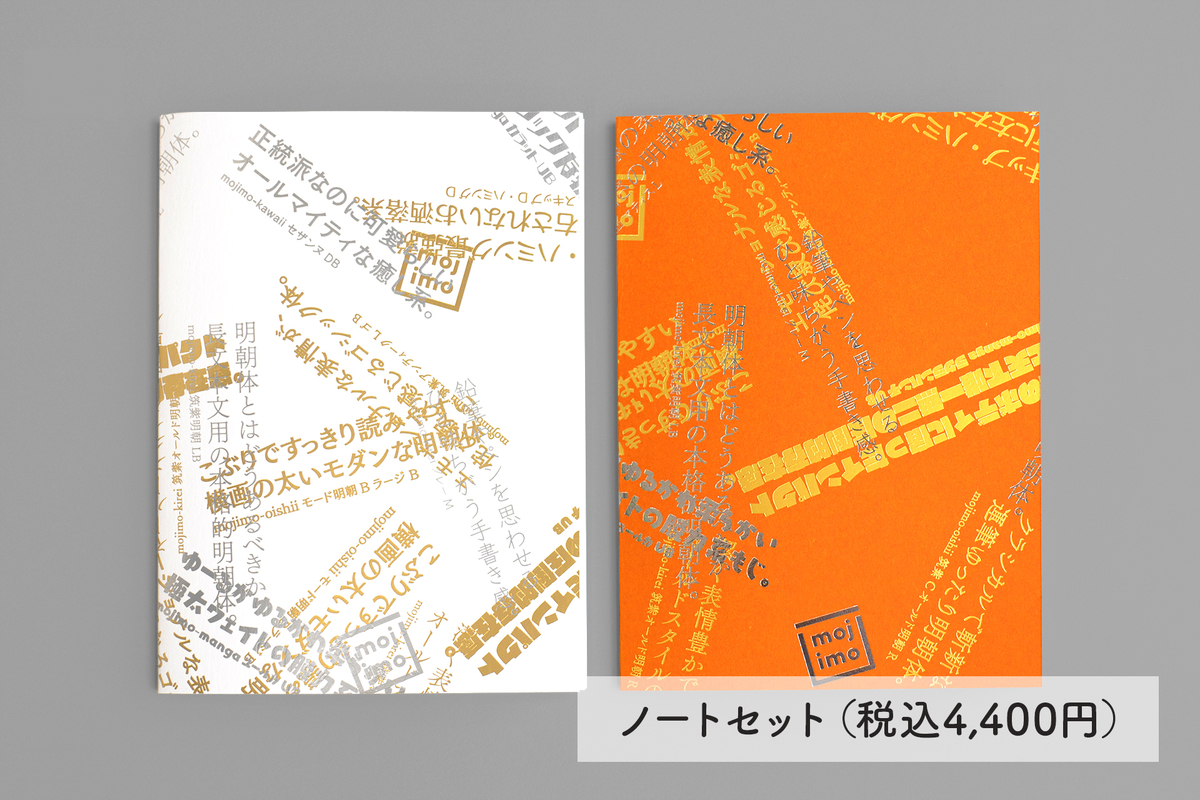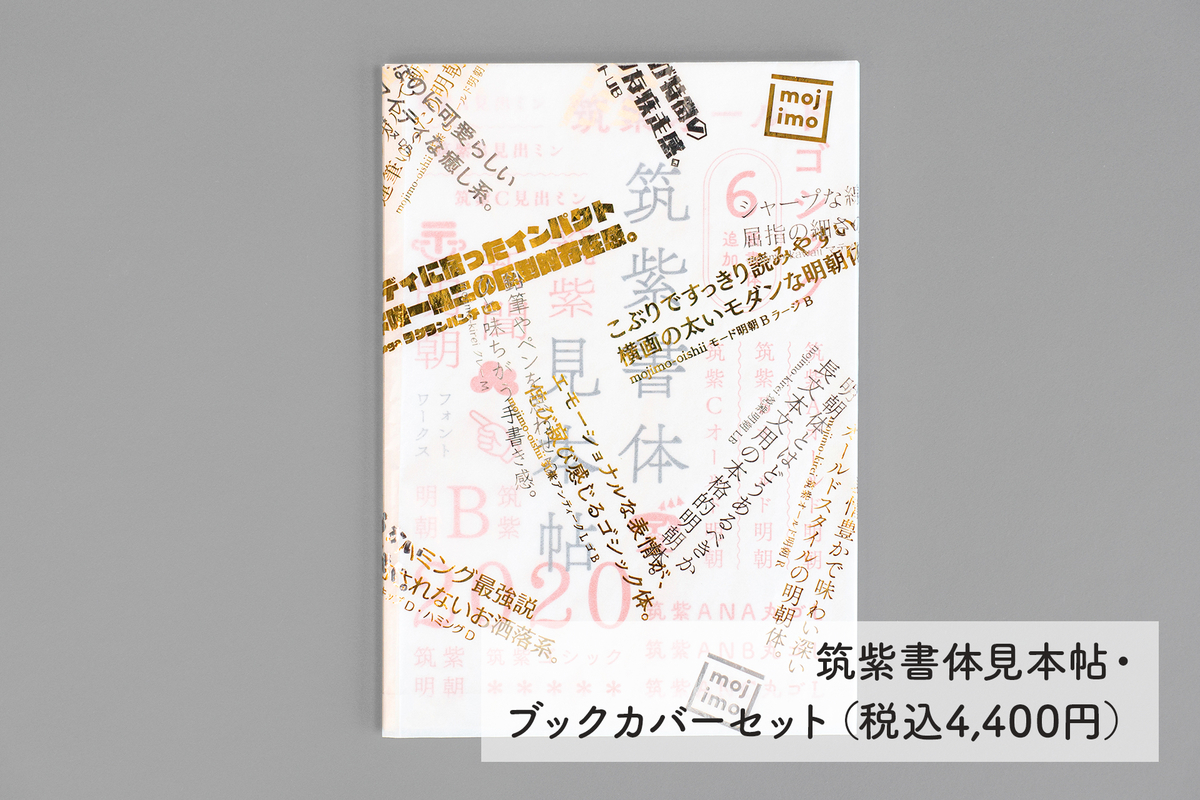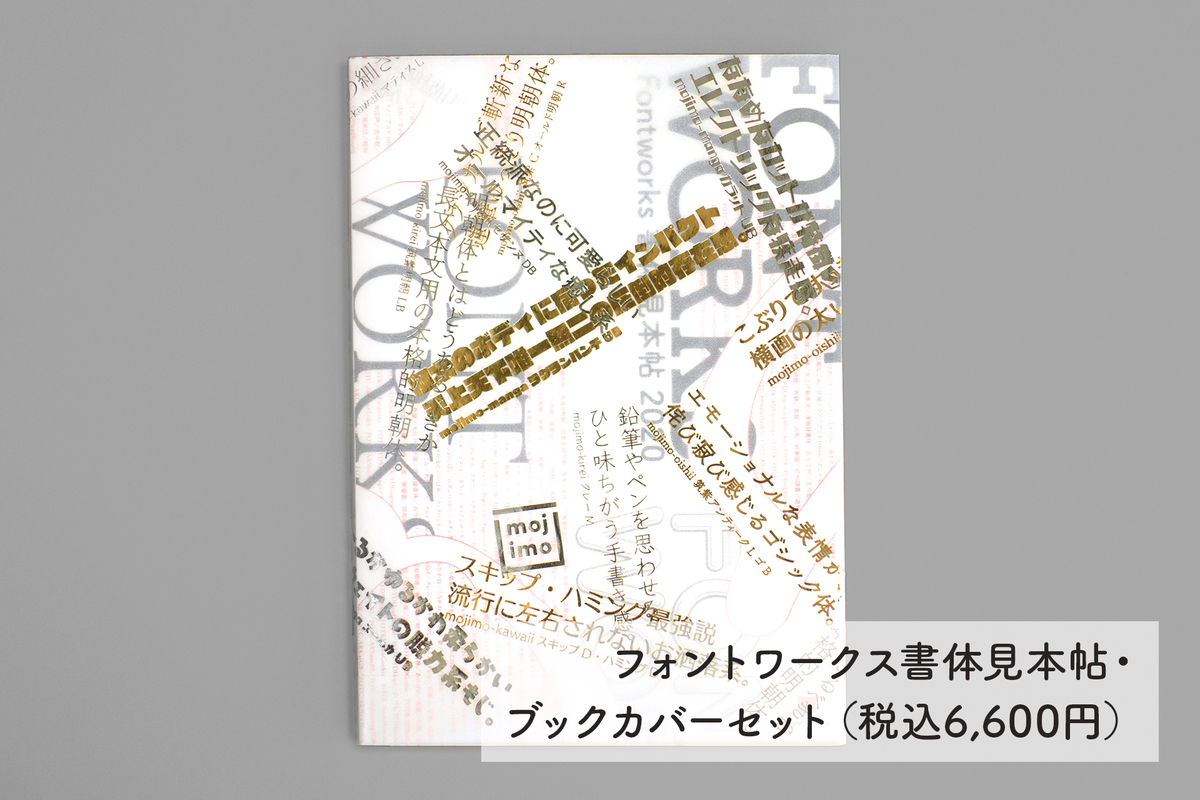
3か月連続提供のラストを飾るmojimo新パック、フォントと箔押しのコラボ文房具
フォントワークスは、セレクトフォントサービス「mojimo」のリリース4周年を記念して、2022年1月より3か月連続で新パックを提供しており、ラストを飾る第三弾として3月31日(木)より、「有限会社コスモテック」とのコラボレーション文房具とセレクトフォントサービス「mojimo」の限定パック提供をクラウドファンディング形式で開始したことを発表した。
また、本施策は、今までフォントに触れる機会がなかった人に「体験・体感」の場を提供し、サービスの良さを「感じて」もらうべくスタートするチャレンジ施策「mojimo-Experience」の第一弾となる。
「文字」を楽しむ仕掛けをちりばめた文房具
小説や雑誌、WEBのニュース記事やブログを読む時に、文字の形をじっくり見たことがあるだろうか?
普段目にする文字(フォント)は、読みやすいように作られているだけでなく、文章の世界観やどんな場面で使われているかなど、TPOに合わせて使用できるように書体デザイナーが考え抜いて作った、いわば「縁の下の力持ち」で、日々の生活に無くてはならない存在である。
本クラウドファンディングは、「文字の魅力」を、普段から手に取るであろう文房具に落とし込んでいる。
リターン品であるオリジナル文房具の箔加工には、コスモテックで保管している箔材・紙を用いてる。
普段なかなかお目見えしないレアリティの高い素材もあり、今回限りの『箔材と紙のおりなす掛け合わせ』を楽しめる。
また、今回の「体験」は、文字の楽しさや箔の美しさを感じられるだけでなく、実際に「文字を使う体験」も提供。
リターン品の文房具に使用した書体が搭載された「mojimoパック」の年間パスコード(1年間)も一緒に届られる。
提供されるオリジナル箔押し文房具
今回のクラウドファンディング施策のためだけにデザインしたオリジナル文房具(全3種)が用意された。
・レターセット(便箋20枚・封筒5枚/1セット)
・ノートセット(2種類/1セット)
・オリジナルブックカバー
ノートの「表紙」、「ブックカバー」はコスモテック現場リーダーによる『ランダム手押し乱れ押し』で施した「一点もの」デザインで届けられる。
また、レターセットの「便箋」や「ノート」には、それぞれの書体から受け取る印象の違いや、フォルムの違いを、目で見て体感していただけるデザインを施した。
注目は、便箋やノートの罫線部分で、文字の連なりで表現されている。
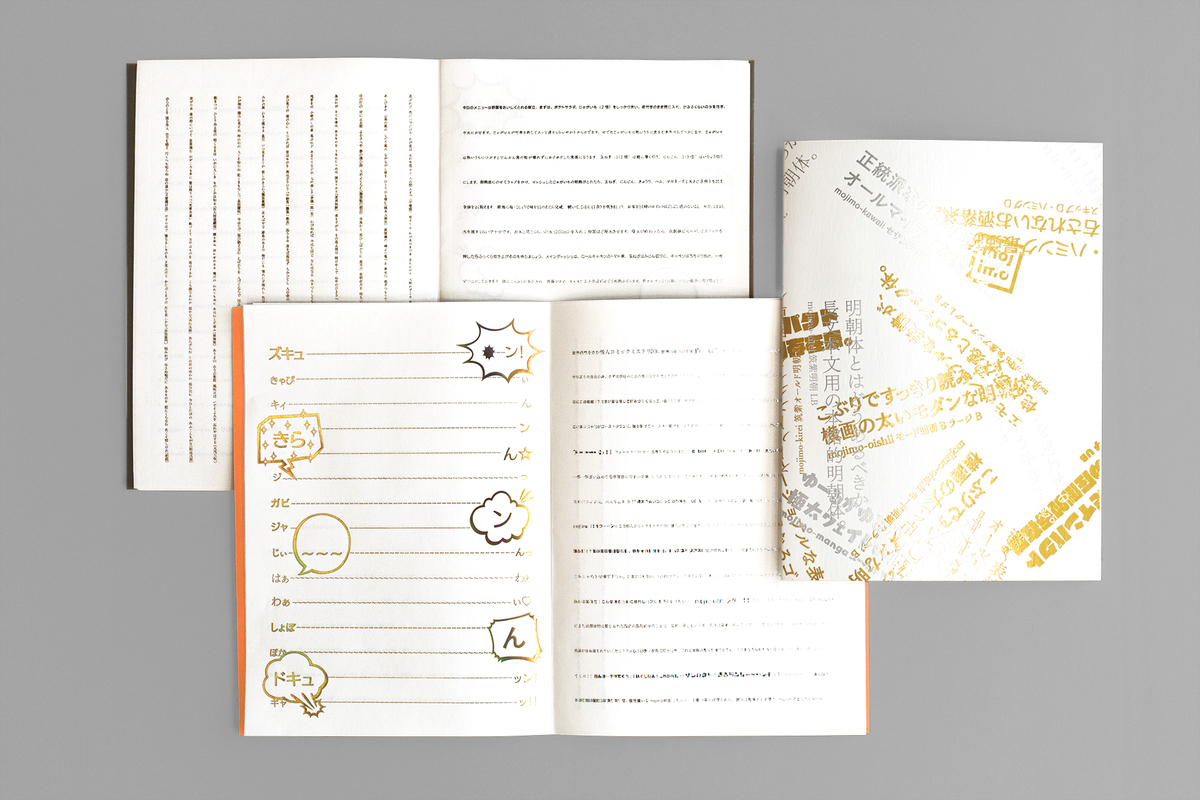
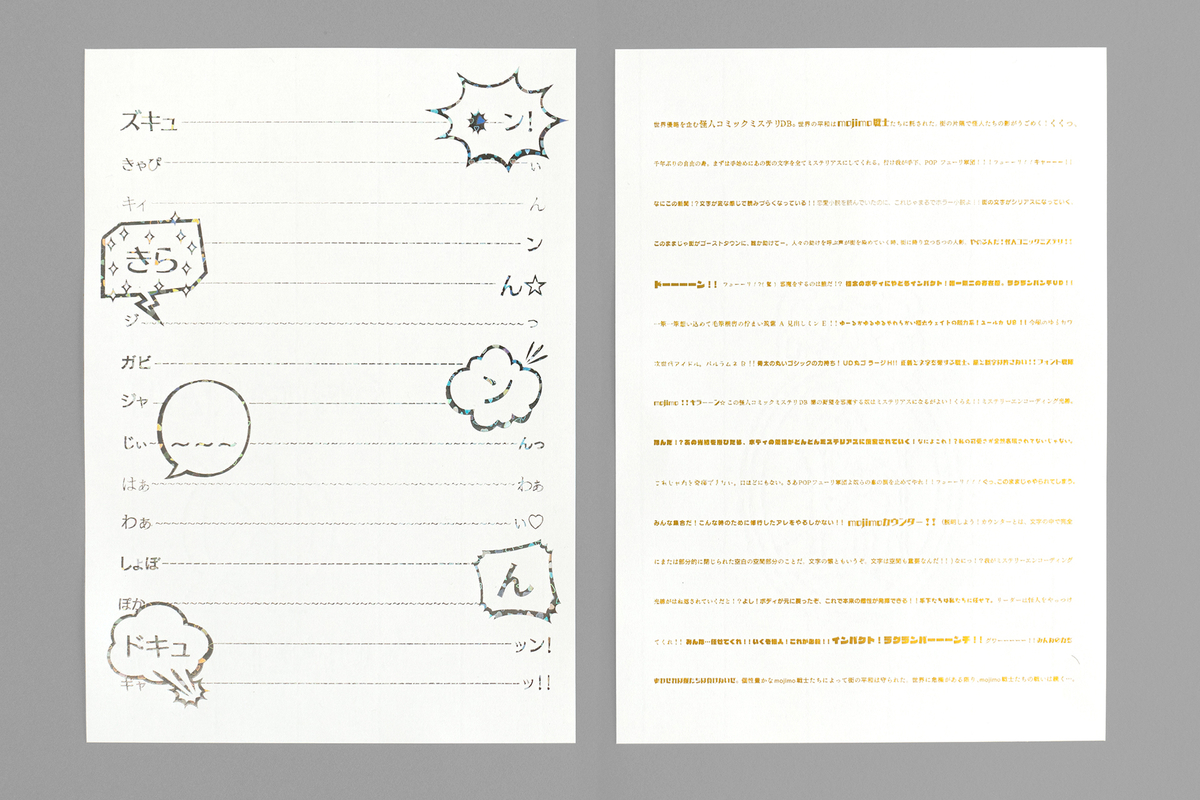
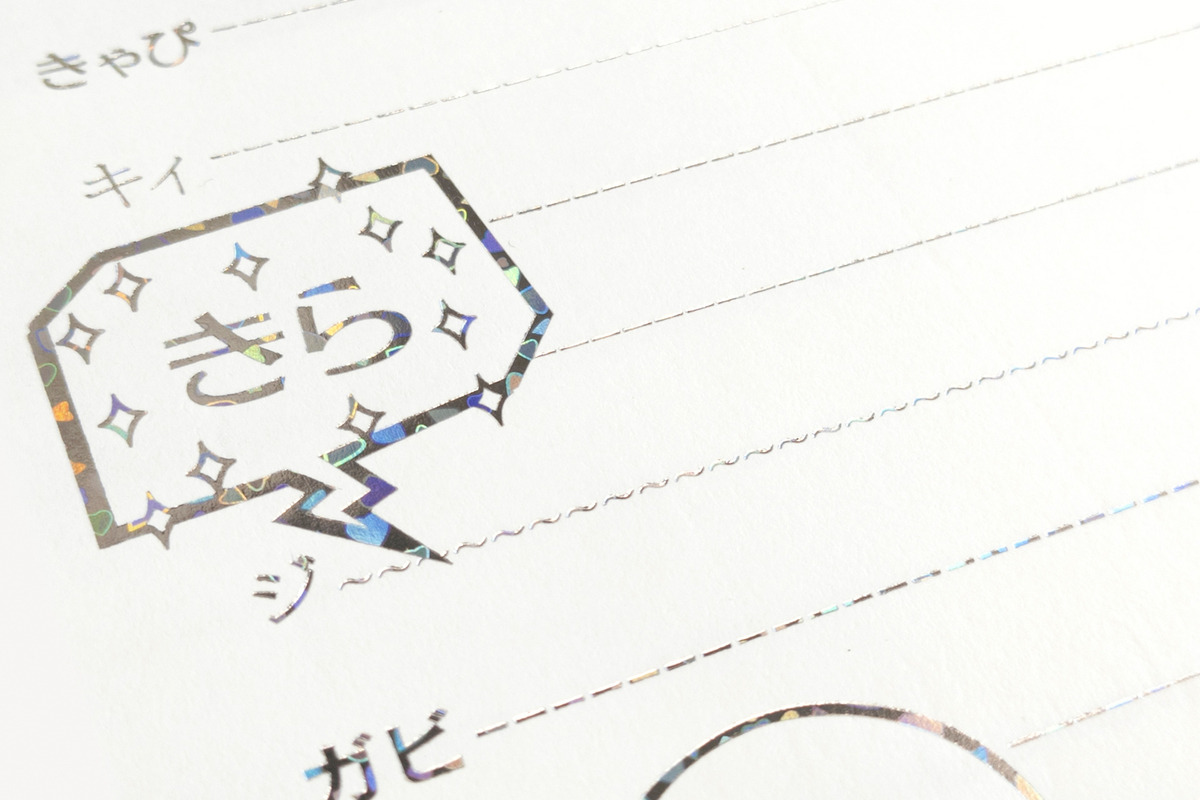
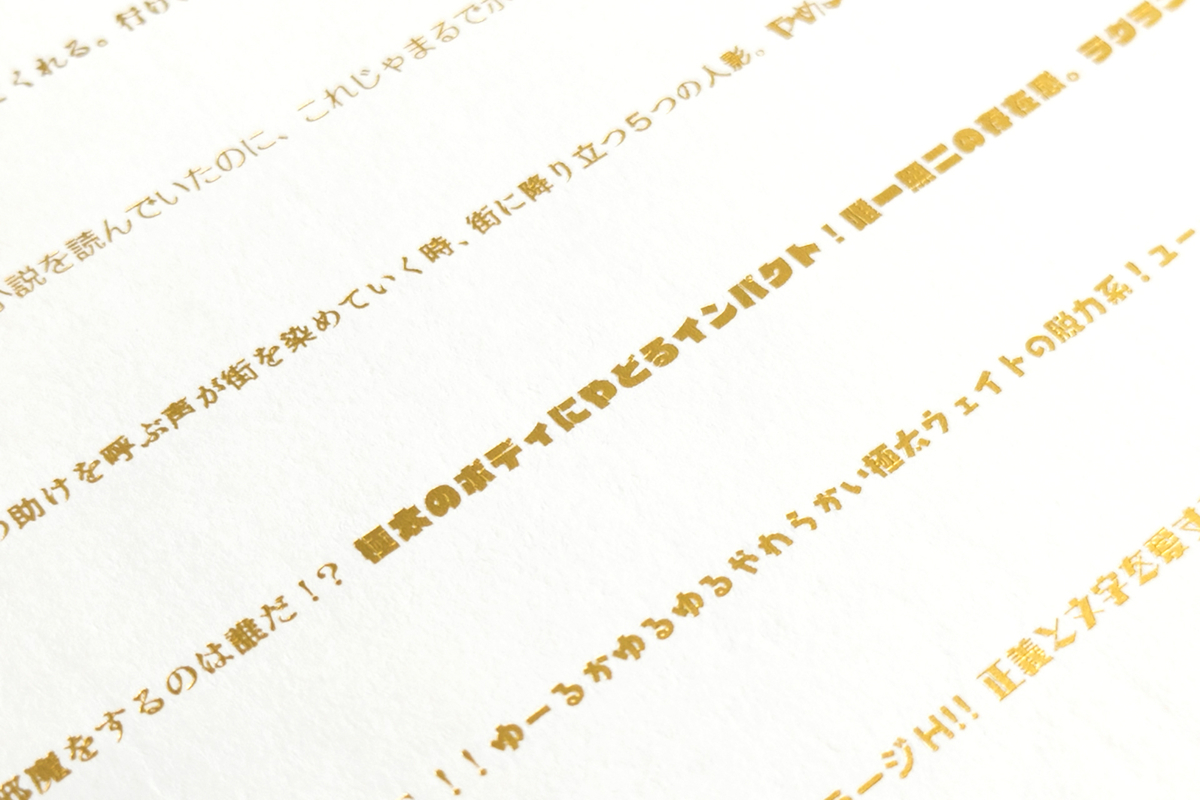
返礼品である「オリジナル文房具」のデザインは、紙と印刷の新しい価値創造に挑戦するデザイン会社「株式会社ペーパーパレード」で、「デジタルとフィジカルの境界を横断しながら紙や印刷の新しい価値を生み出すこと」をテーマに活動している。
mojimo-Experienceとは
「mojimo-Experience」とは、文字通り、今までフォントに触れる機会がなかった方に「体験・体感」の場を提供し、サービスの良さを「感じて」もらうべくスタートするチャレンジ施策となる。
第一弾では、「文字の楽しさ」と「箔押しの美しさ」 を伝えるため、「有限会社コスモテック」とコラボレーションする。
mojimo-Experience 第一弾:文字の楽しさをすべてのひとに届けたい!フォントと箔押しのコラボ文房具 プロジェクト概要